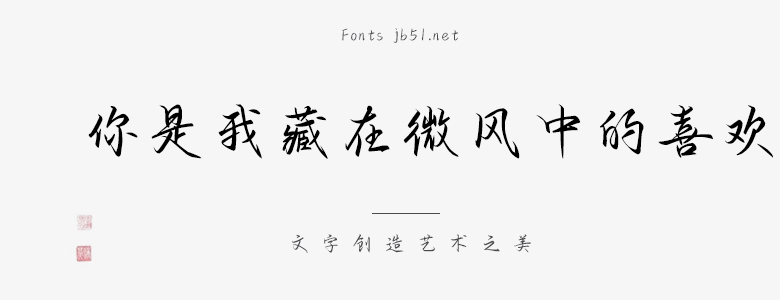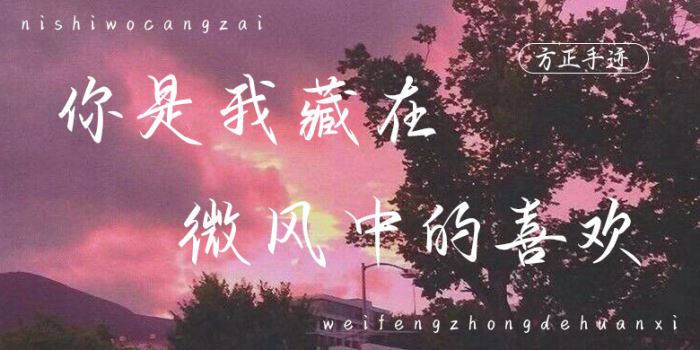
方正手跡-你是我藏在微風中的喜歡由方正字庫余丹設計師出品的藝術字體,字體筆觸適中,字體筆畫既有手寫硬筆字的感覺又不乏軟筆字的特性,適合應用于藝術設計、平面宣傳設計、網(wǎng)頁設計,書法等領域。
你是我藏在微風中的喜歡是一款用手繪板筆刷書寫的字體,字體筆畫既有手寫硬筆字的感覺又不乏軟筆字的特性,字形優(yōu)雅,連筆婉轉流暢,讓人賞心悅目,眼前一亮。適用于文藝類的書刊、品牌廣告和產(chǎn)品包裝設計,以及社交網(wǎng)絡的個性化用字。